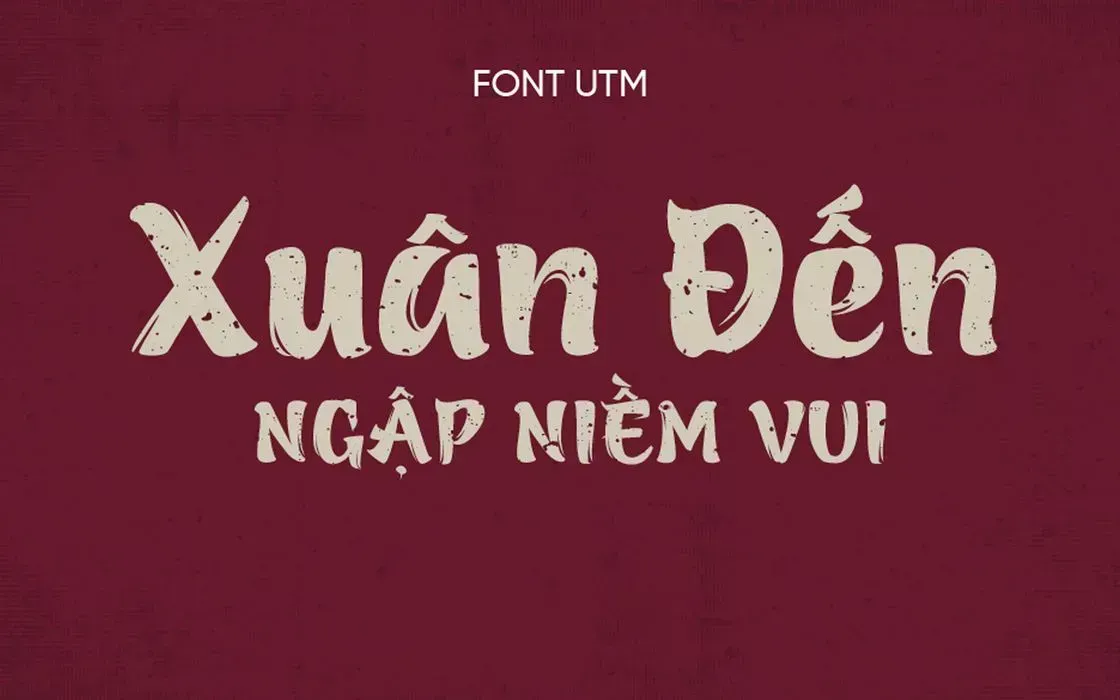
UTM Azuki là một font chữ brush (nét cọ) mang đậm tinh thần ngẫu hứng và phóng khoáng. Các nét chữ mô phỏng cử động tay cầm cọ đầy sinh động, kết hợp giữa đường nét đậm – mảnh tạo nên hiệu ứng thị giác mạnh mẽ. Từng ký tự như được vẽ tay thủ công, mang theo một dòng chảy cảm xúc rõ rệt, rất thích hợp cho những thiết kế cần thể hiện cá tính, năng lượng sáng tạo hoặc cảm giác nghệ thuật đậm chất thủ công.
Font có cấu trúc hơi phá cách, không tuân theo lưới chuẩn truyền thống, điều này làm tăng tính “organic” (tự nhiên) và phù hợp tuyệt đối với các thiết kế như: poster sự kiện nghệ thuật, bìa sách, thiết kế bút ký, bao bì mỹ phẩm thủ công, hoặc các thương hiệu handmade.
Font gốc Azuki Brush được phát triển bởi Toshi Omagari, một nhà thiết kế font nổi tiếng người Nhật, thường lấy cảm hứng từ nghệ thuật viết tay phương Đông và kỹ thuật vẽ truyền thống. Font được đánh giá cao bởi khả năng truyền tải cảm xúc rõ ràng qua từng nét chữ.
Phiên bản Việt hóa UTM Azuki được thực hiện bởi nhóm Urban Type Management (UTM) – chuyên gia Việt hóa font hàng đầu tại Việt Nam. Bản Việt hóa này đã được bổ sung đầy đủ dấu tiếng Việt, giữ nguyên phong cách cọ tự do của bản gốc và đảm bảo tương thích tốt với các phần mềm thiết kế như Illustrator, Photoshop, Canva...